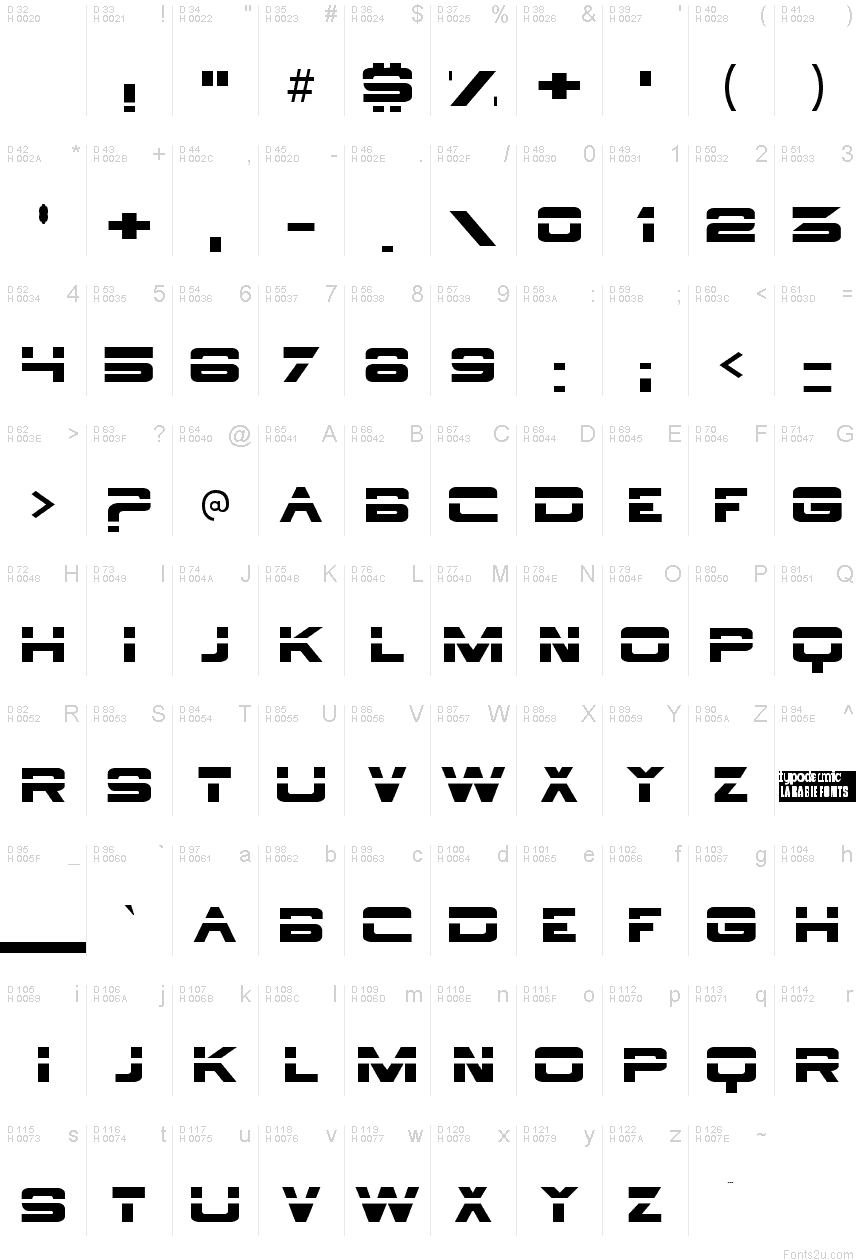
Borg 9 من تصميم Ray Larabie هو خط عرض (Display) مجاني ذو طابع مستقبلي، بحروف تبدو ككتل صلبة مصنعة آلياً. الأشكال السميكة والمربعة مقطوعة بفتحات أفقية نظيفة، مما يجعل الكلمات تبدو وكأنها منحوتة من قطعة معدنية ومضاءة من الداخل. المسافات الضيقة تحافظ على العناوين مدمجة ومؤثرة، مما يمنح تصاميمك حضوراً جريئاً بطابع الخيال العلمي دون أن تبدو فوضوية.
باستخدام Borg 9، يمكنك تصميم شعارات الألعاب، وملصقات أفلام الخيال العلمي، وعناوين الفعاليات التقنية، وتغليف الأدوات الذكية، والرسوم المتحركة (Motion Graphics)، ونماذج الواجهات، وكلها ستشترك في نفس الصوت الصناعي المستقبلي. هذا الخط المجاني يتألق عند استخدامه بأحجام كبيرة، حيث يمكن لهندسته المكتنزة وفتحاته أن تتنفس حقاً؛ وللنص الأساسي، قم بإقرانه بخط هندسي بسيط بلا زوائد (Sans Serif) للحفاظ على الحدة والوضوح.